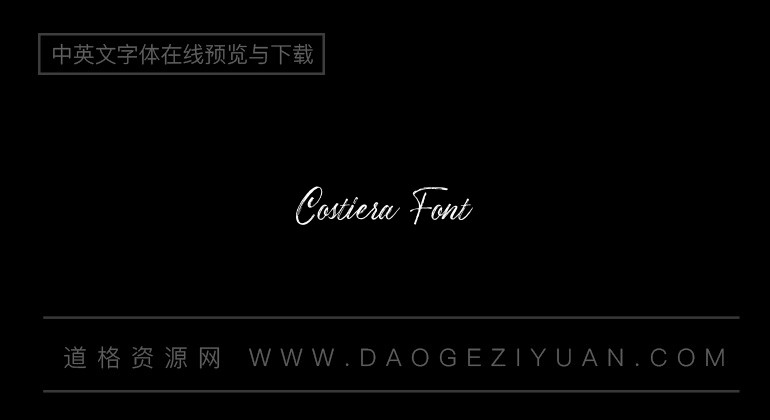
Costiera Font
Costiera Font是一种手写风格的字体,由Jonathan Fabregas设计。它的设计灵感来自于意大利海岸边小镇的手写标志和海报。该字体具有非常独特的个性化风格,使其非常适合各种品牌和设计项目。 Costiera Font字体包括大写字母、小写字母、数字和标点符号。它是一种手写风格,每个字母都有独特的笔画和细节,使其看起来非常自然和真实。该字体具有多种粗细程度可供选择,同时还包括斜体和粗斜体版本。 Costiera Font字体在海报设计、包装设计、广告和标志设计等项目中非常受欢迎。它非常适合需要表达个性化和温暖感的设计风格。
Costiera Font是一款非常不错的手写艺术字体,具有很好的视觉感,适合于文化类的宣传设计、商业类品牌的广告和产品包装设计以及个性化文字排版等较多场景。